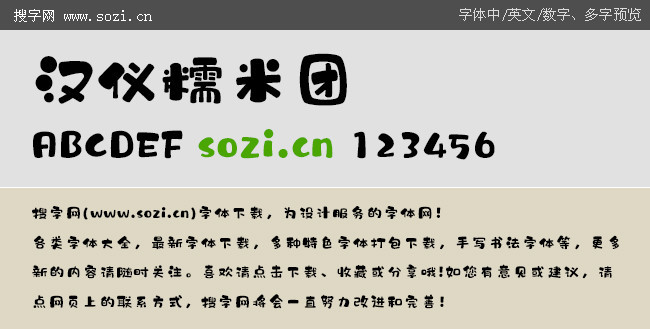
漢儀糯米團(tuán)
搜字網(wǎng)給大家提供一款漢儀糯米團(tuán)中文字體下載。漢儀糯米團(tuán)筆觸較為粗實(shí),字形圓潤(rùn)可愛(ài),適合應(yīng)用與藝術(shù)設(shè)計(jì)、平面宣傳設(shè)計(jì)、網(wǎng)頁(yè)設(shè)計(jì)、海報(bào)設(shè)計(jì)等應(yīng)用。(本字體為個(gè)人非商用版,如需要商用請(qǐng)聯(lián)系漢儀公司購(gòu)買版權(quán))